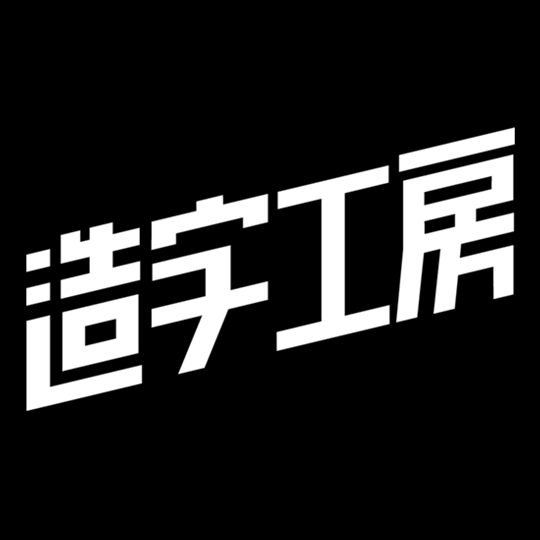
造字工房创建于二零一零年,专注于汉字新字体字形设计与开发。整个设计团队成员由从事多年商业设计的平面设计师和专业字体设计师组成,我们对汉字持有深厚的感情,多年来一直致力于汉字字体字形的设计、应用和研究。
个性化的创意时代,汉字字体字形的设计也正面临革新发展。造字工房的成立,既是担负这份使命与责任,专注为客户在品牌推广方面提升视觉优势,从而直接影响企业品牌的价值提升。努力帮助视觉设计师在设计过程中有更多的优秀字体选择,使其更快更好的完成设计项目。
汉字的美妙之处不仅有形有体,更在于其有骨有肉、有情有意,其形态千变万化却不离其宗,生动之处或静或动,或飘逸或雄浑……一套大陆常用简体汉字字体,其字符集数量高达上万个汉字,每一款美术字体的设计都是一项大工程,设计开发周期动辄一年半载,倘若进行更多深入细节研究与设计,每个设计组开发一款字体最少花费一到两年的时间。汉字作为社会视觉形象的重要元素之一,其形态的设计、应用和发展,更直接影响各行业品牌的巩固和推广。但因着国内汉字字体设计事业发展缓慢,新颖优秀的汉字字体产品日益匮乏,以及随着用户需求和审美的提升,我们越加有责任为汉字字体的设计发展付出更多努力。
我们曾成功为时尚传媒集团设计开发了国内第一款以企业名称命名的字体时尚中黑简体。不仅为品牌的建立和拓展带来良好的社会影响,更在其品牌的视觉形象推广方面形成唯一性,同时保护其品牌的独创价值。我们也与电影《黄金时代》合作开发专用字库产品,并相继自主设计研发出183种251款中文字库产品,包括造字工房悦黑系列字体、造字工房俊雅锐宋体、造字工房尚雅准宋体、造字工房锦宋体、造字工房摩登体、造字工房文雅体、造字工房力黑体、造字工房明黑体、造字工房情书体、造字工房可可体、造字工房童心体、造字工房静黑体等等,一款款字体越来越得到用户的青睐和采用,得到了社会的极大认可。造字工房也以脚踏实地、保持原创的设计精神,不断在字体设计创新领域开拓,每年都会推出更多时尚个性、与众不同的汉字字体产品,努力在中国设计行业中占得一席之地。并将逐渐丰富的字库产品为中国品牌的建立与发展起到推进的作用,更为中国设计师群体的实质工作带来创作上的便捷与进步。